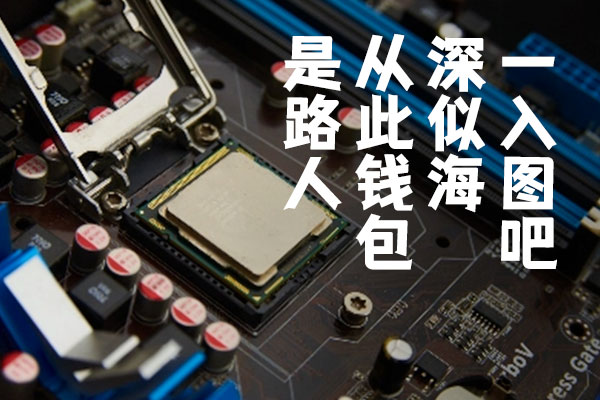
仓耳与墨
仓耳与墨字体是仓耳字库发布的一款免费字体,拥有5种字重,以现代创意风格为主导,强调厚重与力量感。字体设计醒目、有力、前卫。
在字体设计中,我们巧妙地融入了篆刻的“刀意”。我们在处理笔形时模仿了篆刻的刀刻痕迹,让字体多了一份独特的艺术感和历史感。为了中和这种“尖锐”的视觉效果,我们在转折和“口”字结构上采用了圆转角的处理手法,使得整个字形显得内方外圆,既保持了字体的独特个性,又增强了其和谐感和易读性。
同时,为了使字体在使用时更加方便,我们不仅在设计英文和标点部分时沿用了与中文相同的设计特点,让中英文混排时风格统一,看起来更为协调,而且在字形结构上也进行了全方位的优化,确保字体在任何情况下都能发挥出最佳的视觉效果。